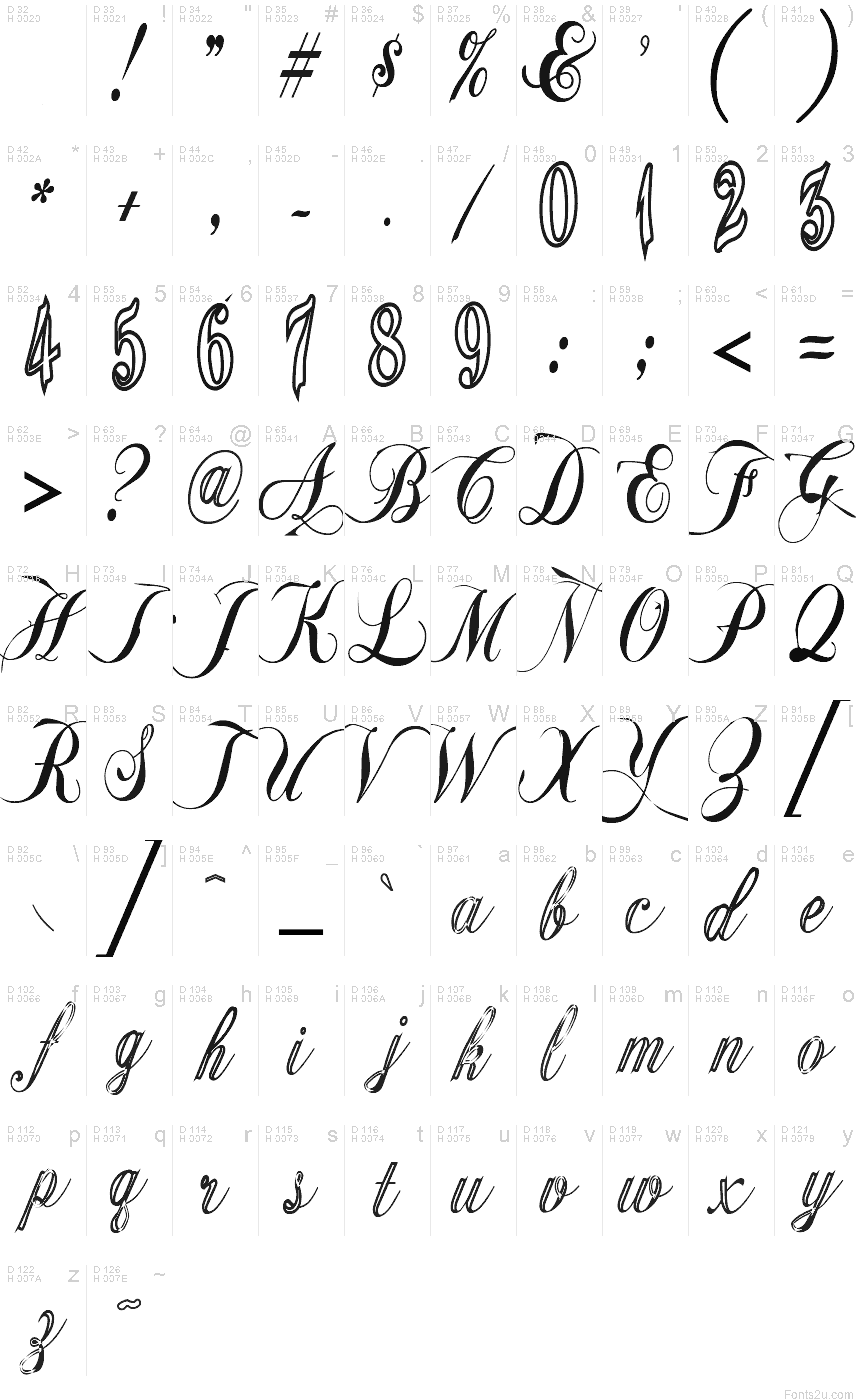
GyiestOld
Citer l'amour sans exprimer son symbole l'criture, mlange de script aiguiser sur des courbes enchanteresse est surement la prsentation sans complexe de cette fonte.